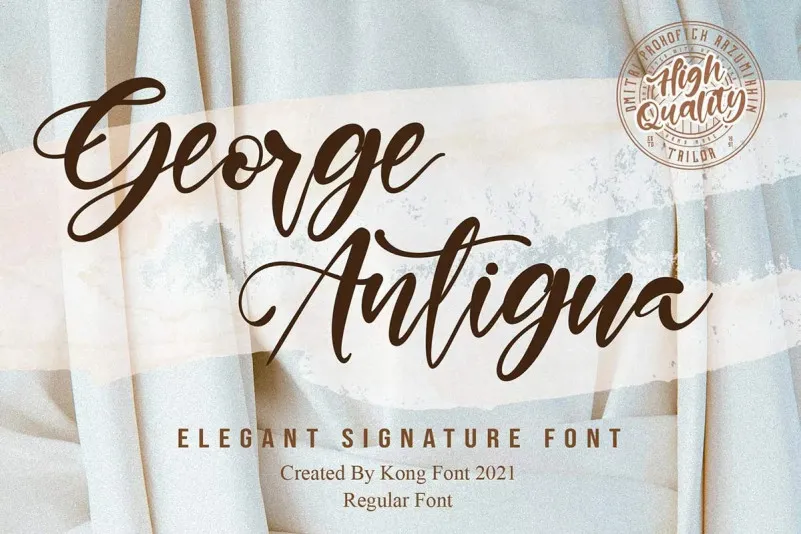
A George Antigua é uma elegante fonte script moderna com detalhes abertos que permitem muitas alternativas e belos esquifes. Esse estilo único combina suavidade e originalidade, tornando-a perfeita para diversas aplicações gráficas. Seu uso em eventos casamento, aniversários, aniversários de nascimento, cartões de convite de festa, logotipos, marca, logotipo elegante, outdoors, embalagens e até mesmo sites, traz um toque autêntico e luxuoso. A George Antigua não só reforça o design dos seus projetos mas também adiciona uma personalidade única que torna cada projeto singular e atraente. Este é um recurso indispensável para designers que desejam dar ao seu trabalho aquele tom de escrita suave e autêntica que faz toda a diferença em qualquer aplicação gráfica.